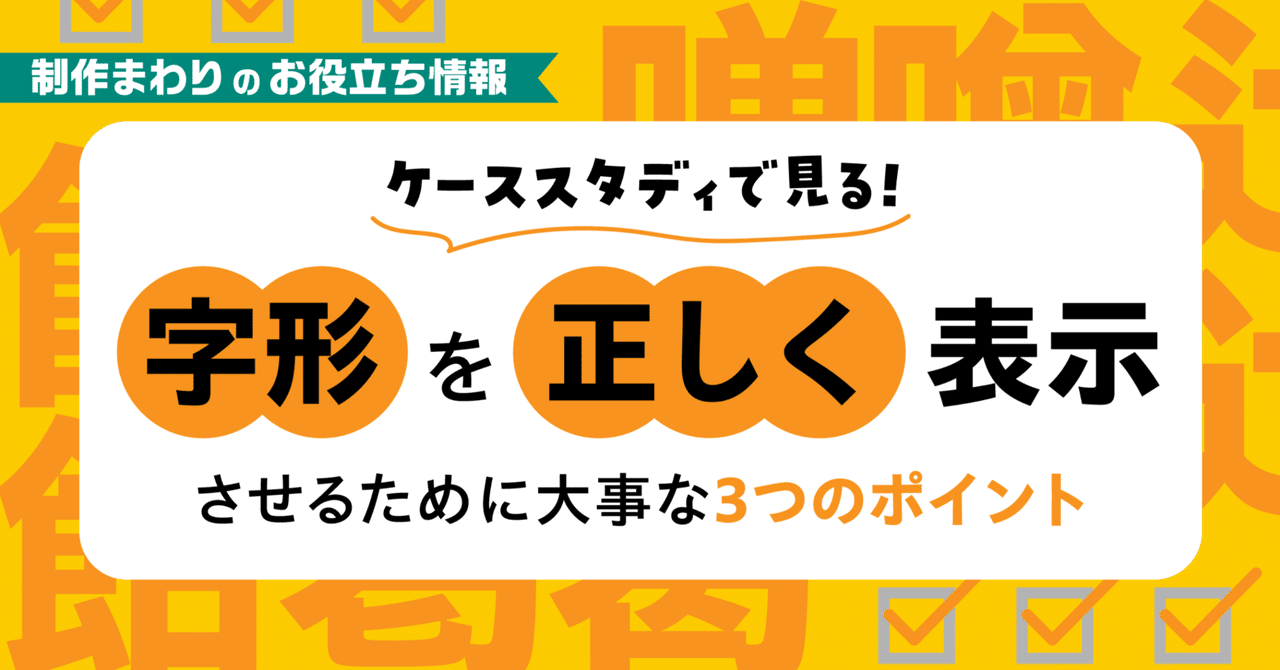
同じ字だけど形が違う?異体字ってなんだろう
漢字の中には、意味や読み方が同じでも文字の形が異なる字が存在し、それを「異体字」といいます。
たとえば兵庫県の宝塚市には「塚」という文字が使われていますが、公式ホームページを見てみると、よく見る「塚」の字より点画がひとつ多い文字の形になっています。
宝塚市 宝塚󠄁市
この「塚󠄁」をPCで入力しようと思っても、Unicode(世界のさまざまな文字をコードで表した業界標準の規格)では、どちらの「塚」も「U585a」というコードが割り当てられており、実際の形は違うのに文字コード上では同じ文字として扱われていますので、PCなどで正しい字体を入力するのは一苦労です。
ささいな違いと思われるかもしれませんが、人名や地名などの固有名詞ともなれば、しっかり正しい文字を表示したいもの。
近年では、ブラウザの表示やフォントが異体字に対応(IVS)したものも増え、Web上で異体字を表示することが可能になっています。異体字の箇所だけ画像を作成して貼り付けるといったことをしなくても、テキストとして異体字を表現できます(この記事中に使われている異体字もすべてテキスト情報をもった文字になっています)。
異体字を入力するには
Web上で異体字を入力するには、文字の後ろに「異体字セレクタ」という符号を記述することが必要になります。
異体字セレクタというのは、異体字が存在する文字に対して、どの形の異体字かを指定するための枝番号のようなもので、Web上で使用するためには、HTMLで任意の文字の後に数値文字参照の形(&#異体字セレクタ;)で異体字セレクタを記述します。
宝塚市? 宝塚󠄁市?
宝塚市?宝塚󠄁市?
異体字を表示するには、フォントが異体字の表示に対応していることも必要となります。
TypeSquareでは「AP版」と呼ばれる書体が対応しており、CSS記述名に「AP」とついている書体を使えば、上記の異体字セレクタを活用いただけます。
例:「Gothic MB101 Regular JIS2004 AP」「Ryumin R-KL JIS2004 AP」など